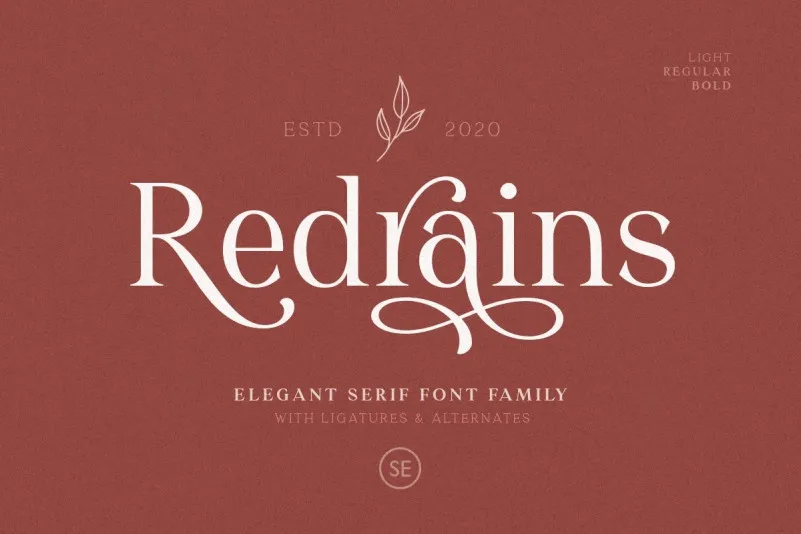
A fonte ‘Redrains Font’ é uma elegante serif que oferece estilo vintage moderno, criada pela Sarid Ezra com três estilos de peso e alternativas para cada caracter e ligatura. Este é um recurso perfeito para aqueles que desejam dar um toque único aos seus documentos ou logos. Com seu design sofisticado, você pode usá-la não apenas como complemento a sua coleção de script, mas também como uma fonte autônoma para múltiplos fins, desde convites de casamento até sua própria marca. Além disso, esta fonte é suportada em várias línguas e está codificada com PUA (Prefered User Access). Ideal tanto para designers profissionais quanto para pessoas que querem dar um toque especial ao seu trabalho pessoal.